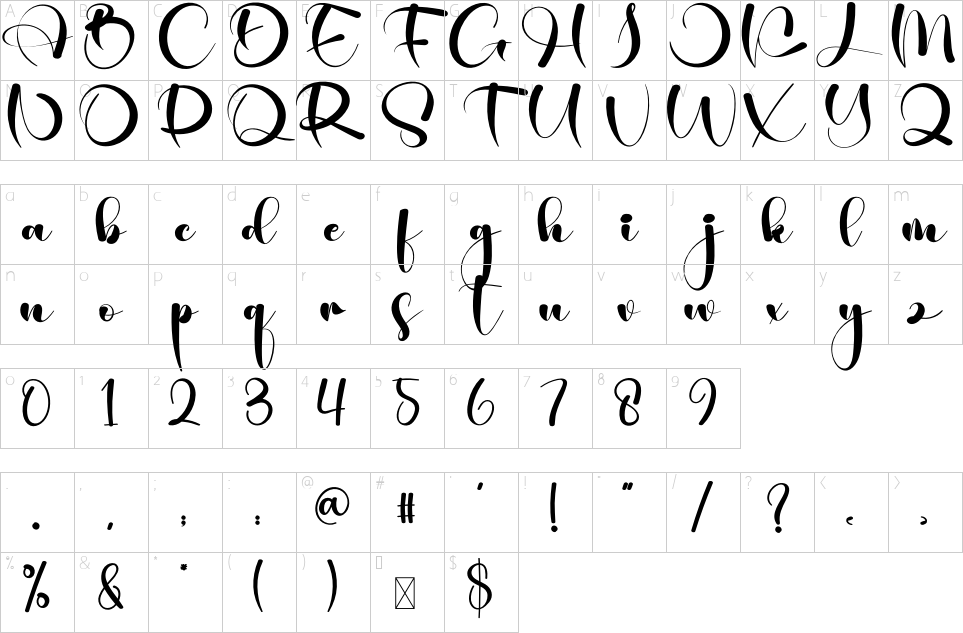
Descubra a delicadeza e a beleza da Angels Font, uma elegante fonte gratuita ideal para seus projetos digitais. Desenvolvida por scratchones, esta font é uma escolha perfeita para adicionar um toque de sofisticação aos seus documentos, relatórios, e-mails ou até mesmo ao design de sua newsletter. As pessoas já se impressionaram com a versatilidade desta font, tendo baixado-a 165 vezes. Estamos felizes por você ter a chance de adquirir Angels Font gratuitamente, uma vez mais, demonstrando que mesmo fontes de alta qualidade podem ser acessíveis e inclusivas para todos. Descubra por si mesmo o brilho desta fonte única e singular.